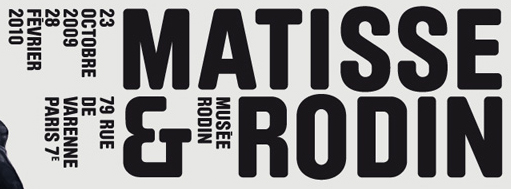
Suche ähnliche Schrift wie BRAUER NEUE
ich suche ganz dringend eine Schrift, die der BRAUER NEUE (Bilder im Anhang) ähnlich sieht, sprich abgerundete Ecken, aber nicht zu Rounded.
Malleable Grotesque Extra
Fishmonger
Atrament Std-Bold
Fono
Ketchupa Pro Regular